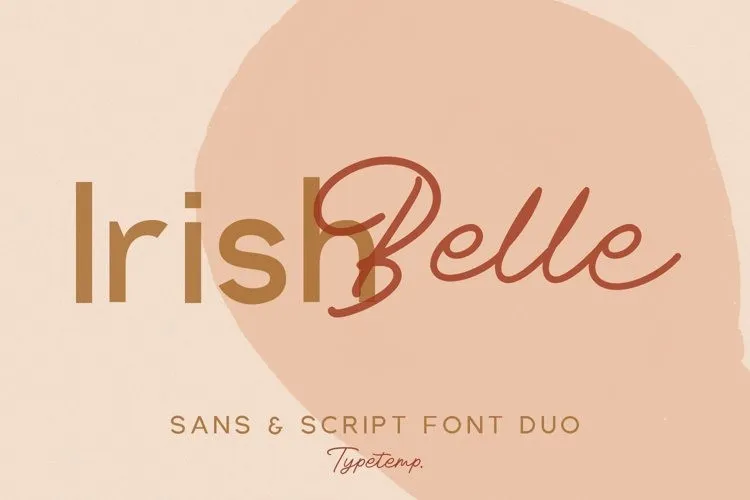
Irishbelle Font Duo – Download Grátis
A Irishbelle Font Duo é uma paixanteira dupla que captura a essência moderna e descontraída do design tipográfico sans-serif. Ela foi criada por Temp Craft, oferecendo uma solução perfeita para aqueles projetos onde você quer transmitir uma atmosfera romântica enquanto mantém um toque casual. Os elementos deste par font são ideais para criar logotipos, roupas, convites de casamento, marcas de marca, anúncios e outros projetos românticos. As Irishbelle Font Duo é uma combinação perfeita que permite ao designer explorar a criatividade através do texto em designs variados sem perder o charme moderno e despojado da Irlanda, com sua forte influência na moda irlandesa.